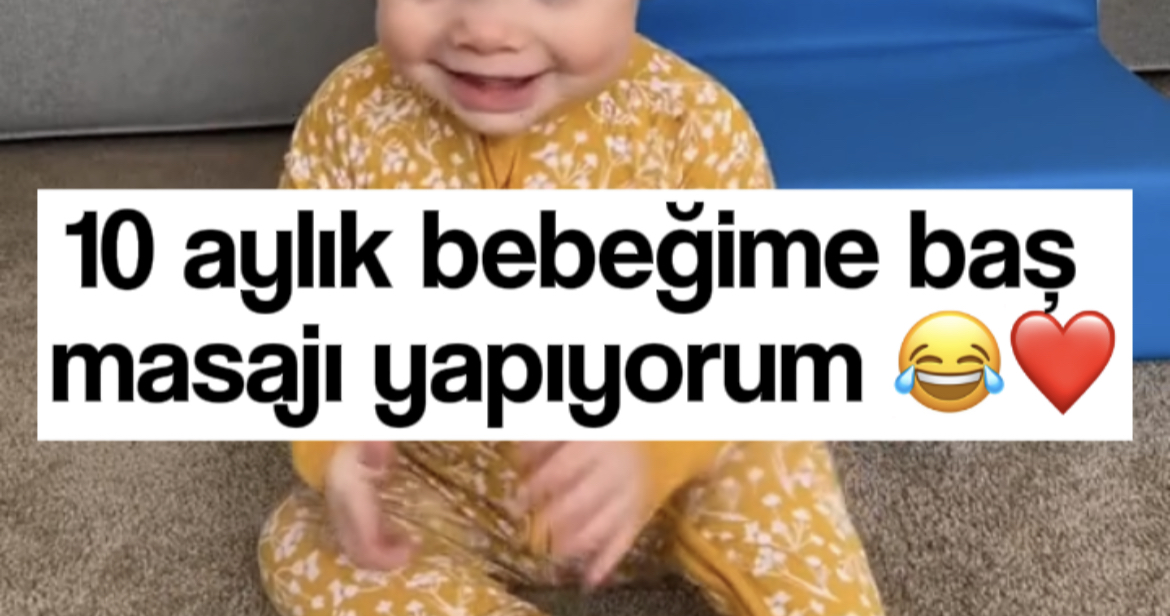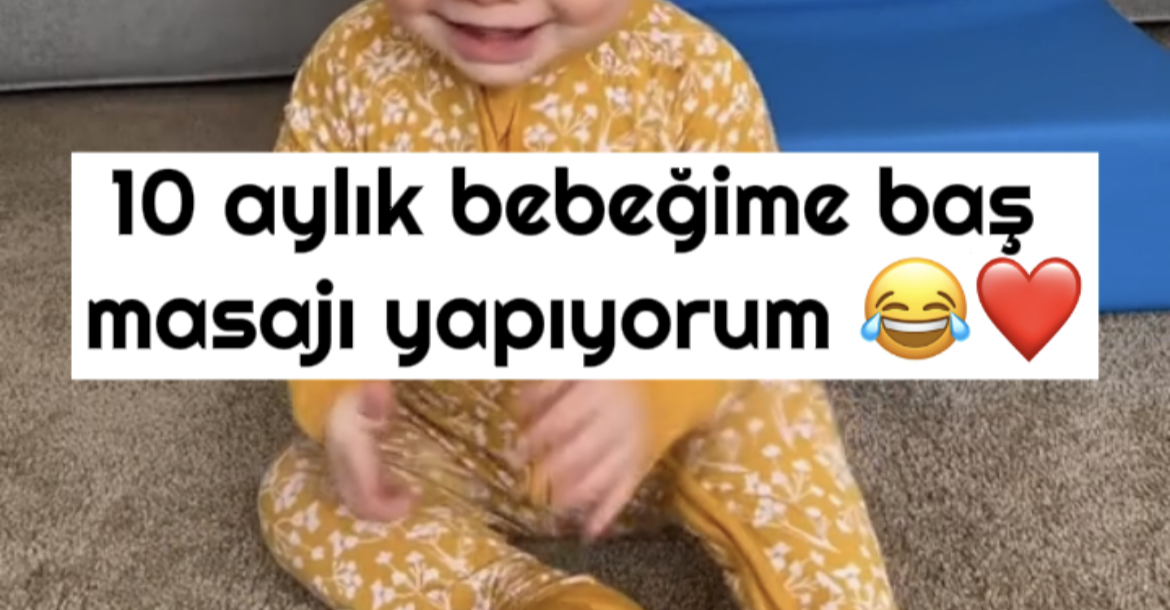
Instagram Videolarda kullanacağım fontlar arasında kararsız kaldım sizce hangisi daha göz alıcı dersiniz? Veya tavsiye ettiğiniz font varsa önerilere de açığım
Üstteki bence hocam
kesinlikle 1 hocam. 2. font çalıntı videolar gibi duruyor.
Üstteki daha güzel
üstteki daha güzel.
Üstteki. Zira ikinci fontun öyle bir etkisi var ki kapakta görsem kesinlikle başka bir şey çıkabilir diyip girmem. Başarılar dilerim. İçerik temsili değilse sevimli şeyler var sanırım 🐣
İlk font göze daha hoş geliyor ve ilgi çekiyor bence ilk fontu kullanabilirsiniz.